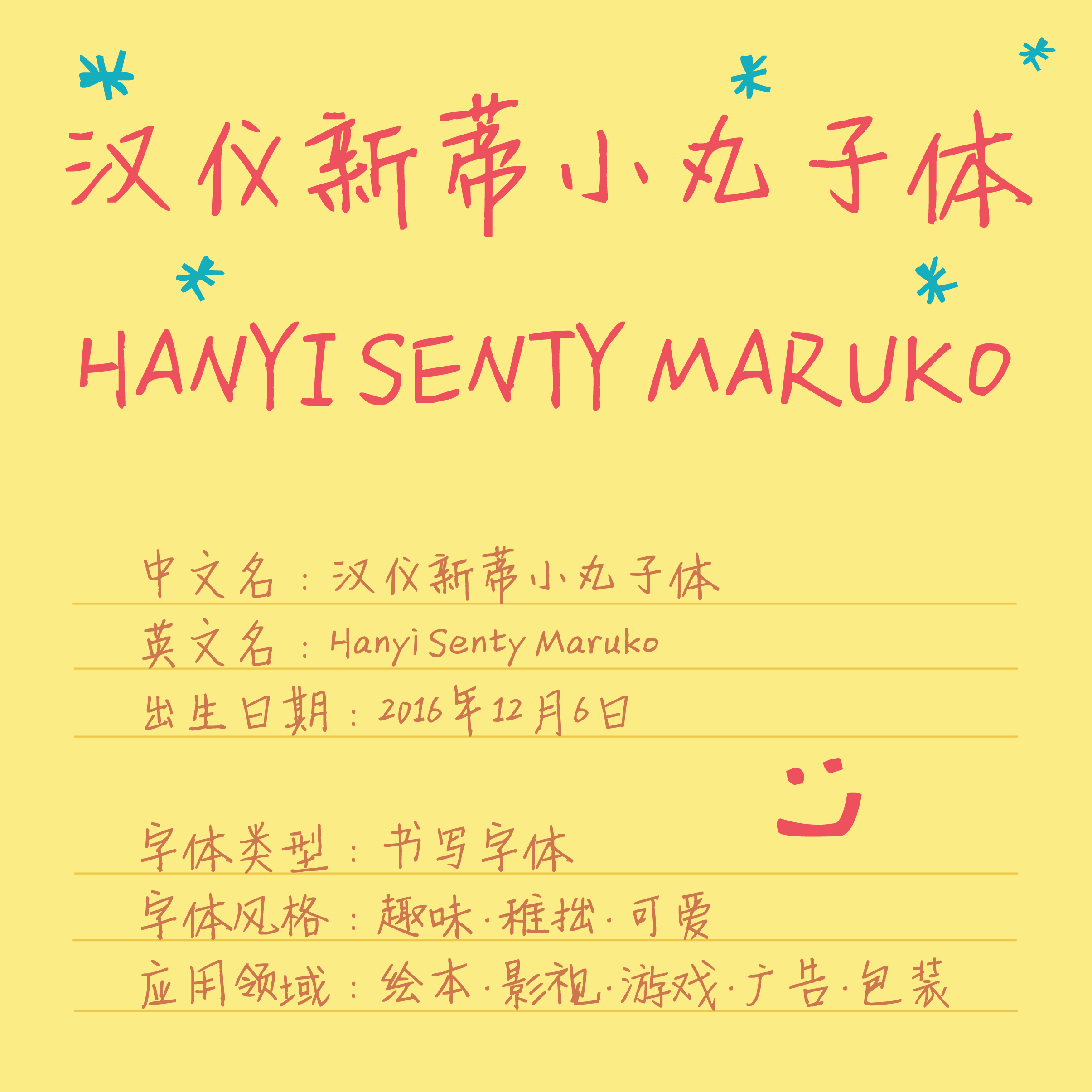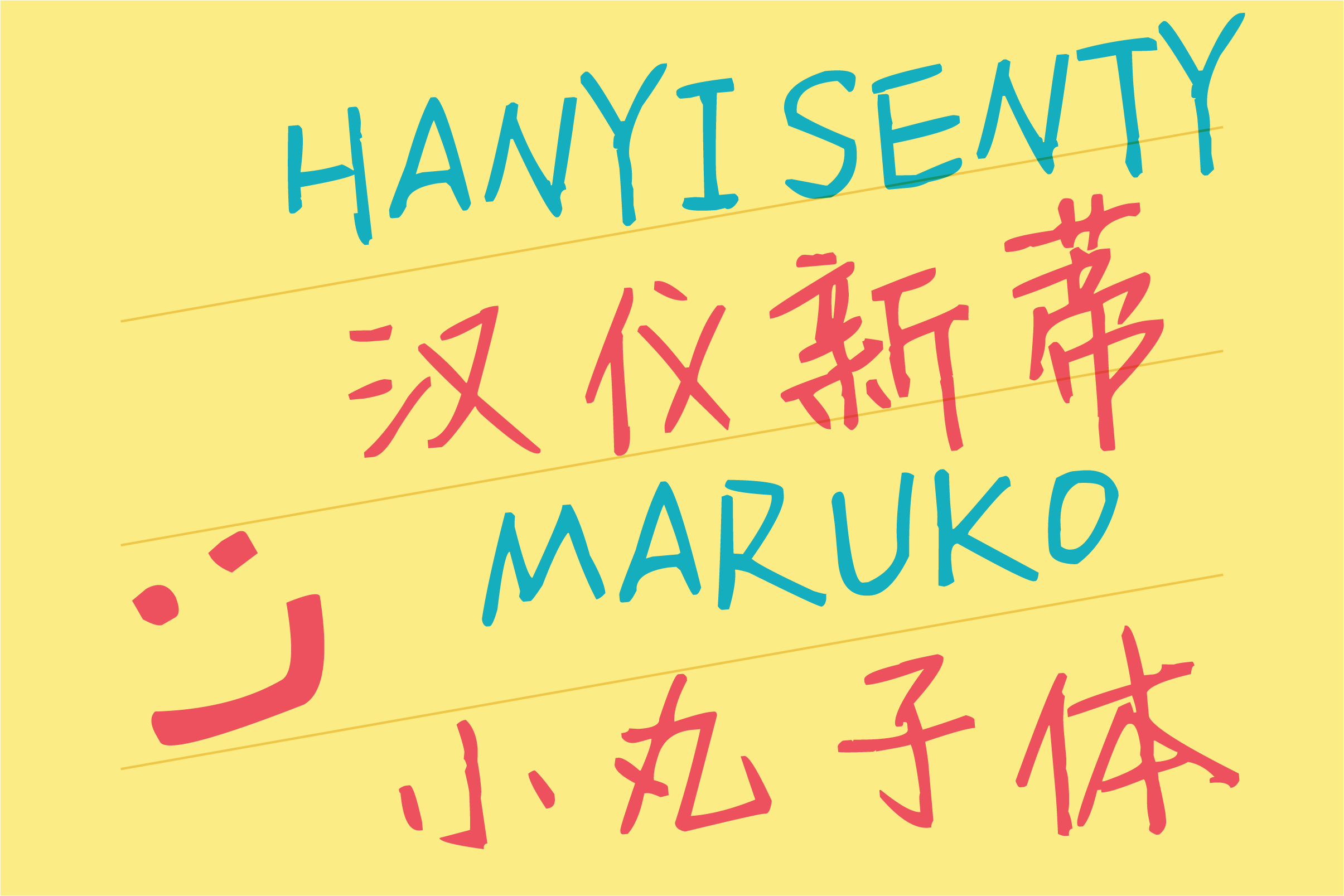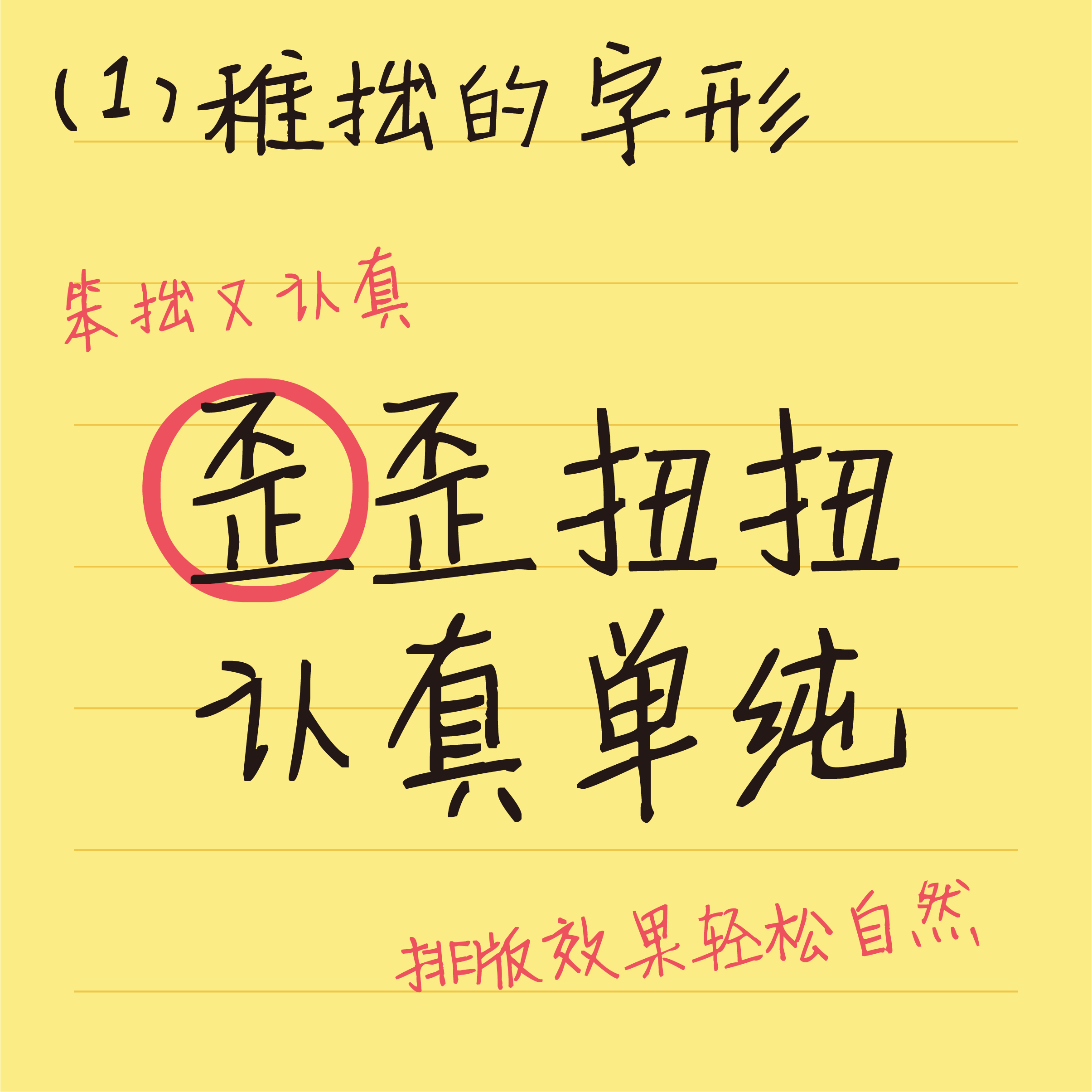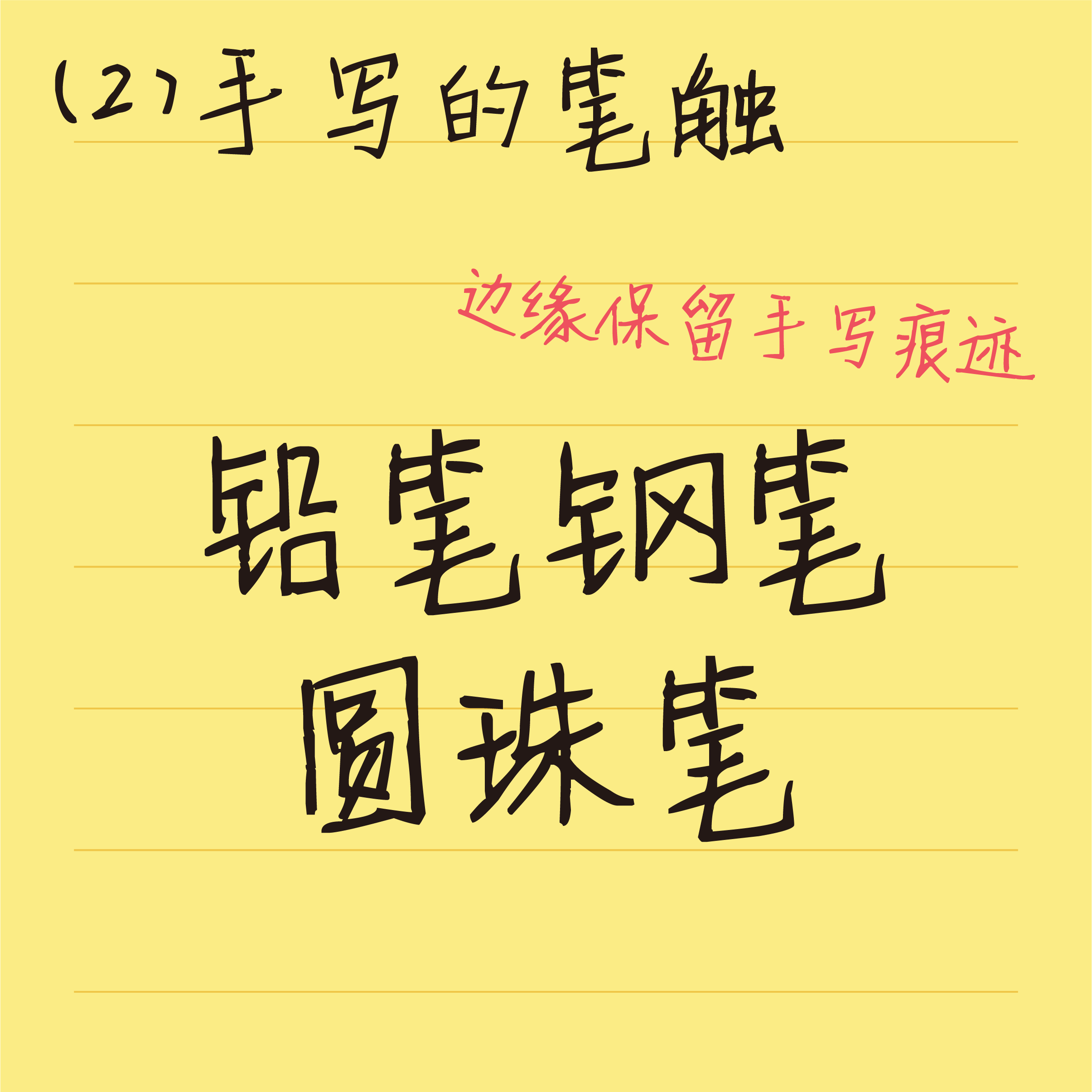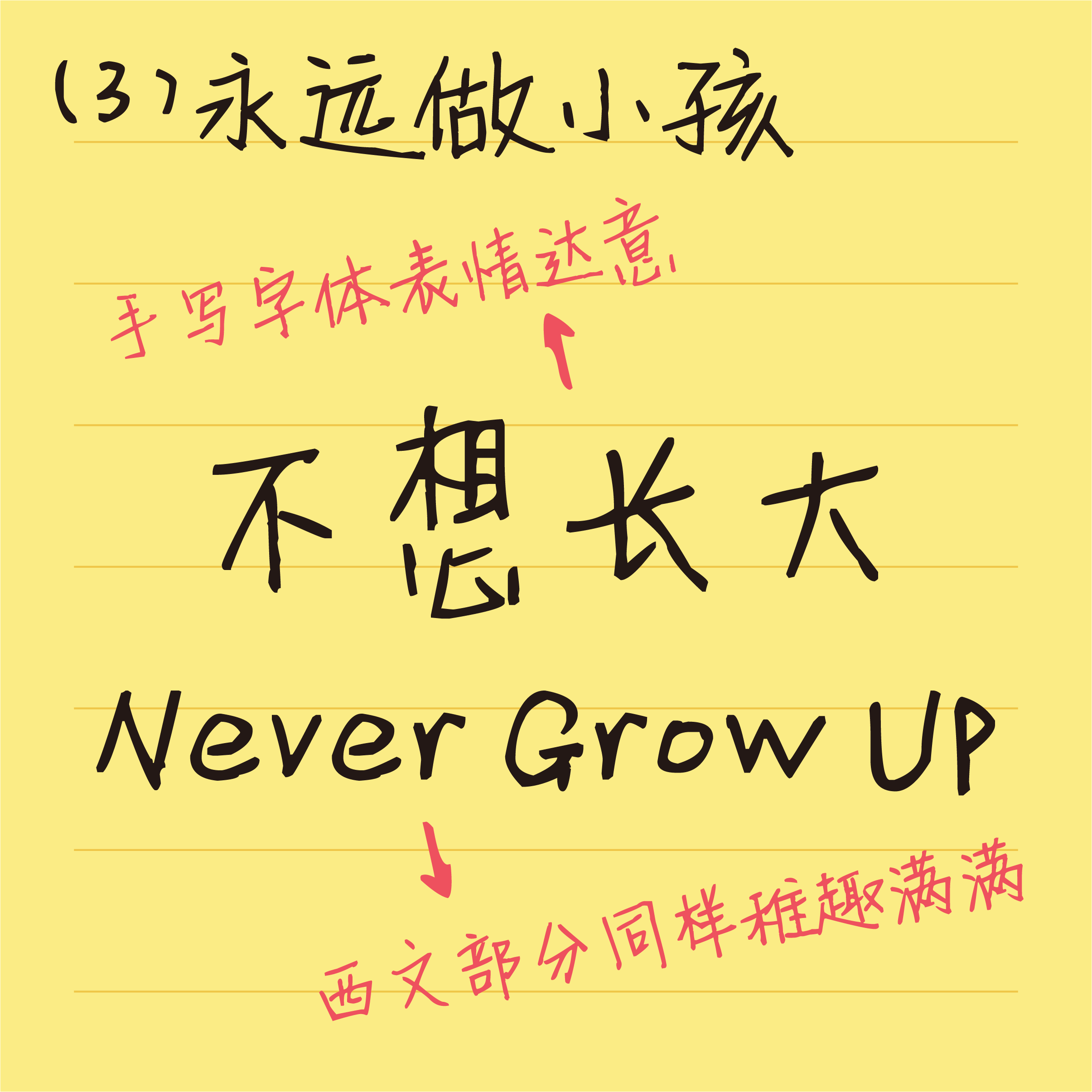
汉仪新蒂小丸子体
童年记忆中的书写,或许是有些稚嫩的、有些笨拙的,却又是认真的、单纯的,汉仪新蒂小丸子体就是这样一款充满了童真趣味的手写字体,稚拙又可爱,唤醒心底那个永远不想长大的孩子。这款字体适合用于漫画绘本、影视动画、广告包装,让文字排版也任性一把,不要长大。
汉仪新蒂小丸子体|字体特征
回到童年的第一步:字形要稚拙可爱。
回到童年的第二步:找回手写的笔触。
回到童年的第三步:以字体表情达意。